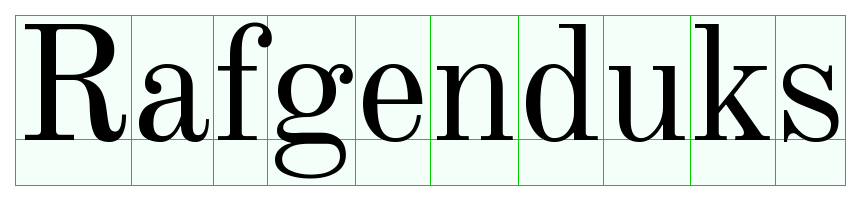
erste eigene Schrift, Anfängerfragen
ich möchte als Praktikumsprojekt für mein Fachabi im Bereich Gestaltung meine eigene Schrift erstellen. Dazu folgende geplante Vorgehensweise:
-Vorüberlegungen, Ideen, Skizzen und Zeichnungen auf weißem Papier
-einscannen der vollendeten Buchstaben, Zahlen und Sonderzeichen
-Bearbeitung der Buchstaben und der richtigen Maße in einem Grafikbearbeitungsprogramm und als Vektorgrafik speichern
-In den Fonteditior importieren und nachbearbeiten/abgleichen/kerning und im richtigen Format speichern
Soviel zur Theorie, trotzdem hab ich noch einige Fragen.
Wie groß sollte ich die Buchstaben auf dem Papier am besten Zeichnen? Ist Bleistift Ok, oder lieber Fineliner, Edding?
Mit welchen Programm sollte ich am besten die eingescannten Buchstaben bearbeiten? Habe sämtliche Programme wie Photoshop CS3, llustrator CS3, Indesign CS3, Freehand MX, ... zur Verfügung.
Muss ich jeden Buchstaben als einzelne Datei speichern? Wenn ja, wie groß? 1000x1000 Pixel? Wie groß muss dann der Buchstabe sein, oder ist das egal solange die Buchstaben verhältnismäßig passen und die Gleiche Unterkante haben? Was ist mit dem Randabstand links und rechts? Hintergrund transparent? Wie mache ich daraus konkret Vektorgrafiken und in welchem Format muss ich speichern?
Da ich leider keinen entsprechenden Fonteditor zur Verfügung habe muss ich hier Freeware einsetzen. Dachte da an Fontforge.
Was muss ich sonst noch beachten? Erklärungen und Tipps wären sehr hilfreich, da dies wie gesagt meine allererste eigene Schrift wird, und ich mich erst noch intensiver in die ganzen Programme, Formate und Strategien reinfinden muss.
Ich werde jetzt mal als Nicht-Schriftgestalter einige Gedanken zum Besten geben, die geschätzten Kollegen werden mich sicherlich korrigieren, falls ich daneben liege :D
-Vorüberlegungen, Ideen, Skizzen und Zeichnungen auf weißem Papier
In meinen Augen könnte es Sinn ergeben, das auf Millimeter- oder zumindest kariertem Papier zu machen; so wird alles einigermaßen gleichmäßig, kann mir vorstellen, dass Dir das anschließend einige Arbeit spart ...
-Bearbeitung der Buchstaben und der richtigen Maße in einem Grafikbearbeitungsprogramm und als Vektorgrafik speichern
Ich vermute mal, dass der eigentliche Fonteditor besser geeignet ist; vermutlich ist die Vektorenbearbeitung hier für diesen Anwendungszweck optimiert :D
Wie groß sollte ich die Buchstaben auf dem Papier am besten Zeichnen? Ist Bleistift Ok, oder lieber Fineliner, Edding?
Je größer du arbeitest, um so besser kannst Du die Details kontrollieren; Comicseiten die später auf A4 gedruckt werden sollen, werden beispielsweise gerne in A3 gezeichnet :D
[...] und die Gleiche Unterkante haben? Was ist mit dem Randabstand links und rechts? Hintergrund transparent? Wie mache ich daraus konkret Vektorgrafiken und in welchem Format muss ich speichern?
Mit der Unter- und Oberkante musst Du aufpassen: Alles was Rund ist, beispielsweise das O, ragt oben und unten etwas über »rechteckige Buchstaben (beispielsweise das x) hinaus, ebenso alles was spitz ist; das A ragt etwas über das X hinaus.
Beim umwandeln in Vektoren wirst Du ums zeichnen mit der Hand nicht herum kommen; Funktionen wie Livetrace oder dergleichen liefern hier sicherlich keine sauberen Ergebnisse, sprich möglichst wenige und sinnvolle Vektoren ...
Wenn ich das richtig verstanden habe, müssen die Buchstaben, die ich in FontForge importiere Vektorgrafiken sein. Das heißt ich muss die eingescannten Buchstaben erstmal irgentwie in Vektorgrafiken verwandeln, und vorallem so, dass alle Buchstaben proportional zueinander passen.
Ich habe auch gelesen, dass es sinnvoll wäre die Buchstaben in eine SVG Datei zu kopieren um durch Hilfslinien die Buchstaben richtig anzuordnen. Wie genau funktioniert das denn, oder ist das garnicht wirklich notwendig?
Ganz sicher bin ich mir noch nicht, aber es geht wahrscheinlich in einem Stil ähnlich Unreal Torunament Font oder Polaroid 22, vielleicht auch eine Mischung aus beidem. Naja, jedenfalls soll es etwas ausgefallener werden und keine stur geradlinige Schrift.
Mhh, das sind schon zwei paar völlig verschiedene Schuhe. Der Polaroid-Font ist ein typischer Autotrace-Font. Da wird ein Scan/eine Bitmapgrafik vektorisiert und dann allenfalls noch etwas »aufgeräumt«.
Wenn du wirklich saubere Umrisslinien haben willst, dann baut man diese eher anhand des Scans komplett neu auf, weil die automatische Vektorisierung immer viel zu viele und falsch platzierte Ankerpunkte erzeugt.
Darüber hinaus: Anfängerfehler Nummer 1 in diesem Zusammenhang: ein Vektor-Illustrationsprogramm hat quasi keine »Auflösung« – die Punkte können überall liegen. Ein Font dagegen hat ein strenges Raster – z.B. 1000 x 1000 Einheiten als Standard bei PostScript-basierten Fonts. Holt man dann die Vektorzeichnung vom Illustrationsprogramm in den Fonteditor wird die Kontur durch die Rundungsfehler teils drastisch durcheinandergewirbelt. An diesem Punkt ist aber schon alles zu spät. Man muss das Raster also schon im Illustrationsprogramm entsprechend anlegen. Oder: Besser gleich direkt im Fonteditor arbeiten. Entsprechende Funktionen für Bitmaps im Hintergrund haben die meisten Fonteditoren.
So, nachdem der Begriff Kegel geklärt ist, nochmal ein Versuch, den Raster zu erklären:
Schriften haben diesen Kegel üblicherweise in 1000 Höheneinheiten unterteilt. D.h. wenn du den Kegel in Illustrator mit 1000mm anlegst, sollest du Knotenpunkte immer nur auf volle Millimeter-Koordinaten legen, denn wenn du den Buchstaben später ins Schriftprogramm importierst, wird auf diese Quaitifizierung gerundet. Liegt ein Knoten auf X/Y 550,6/103,2mm, dann wird er auf die Koordinaten 551/103 verschoben. Je nach Entwurf und Konstellation (spitze Einläufe, ...) ist diese Rundung durchaus sichtbar und störend.